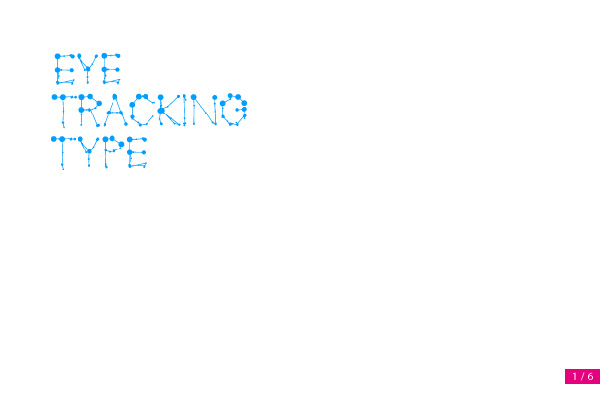
Eye Tracking Type Die „Eye Tracking Type“ ist eine personalisierte Schrift, frei von Stift und Zettel. Dazu werden Augenbewegungen von verschieden Probanden mit Hilfe von Infrarotkamera aufgenommen. Die Bewegungs-Visualisierungen werden anschließend vektorisiert und in einem Schriften-Editor bearbeitet, so dass sie einfach eingetippt werden können. Christoph Mäder, Matthias Rauber www.eyetrackingtype.de |